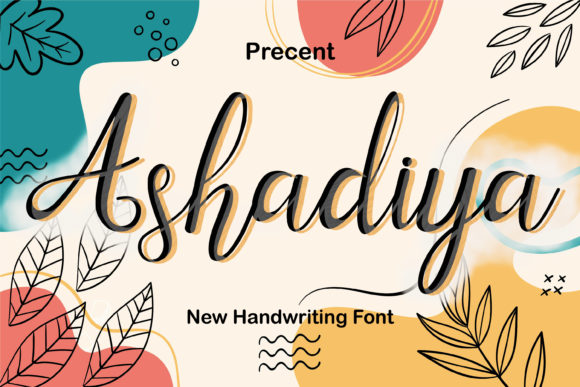
Ashadiya
Ashadiya – A Fonte Script Elegante para Todos os Seus Projetos
Se você busca uma tipografia que combine sofisticação, legibilidade e versatilidade, Ashadiya é a escolha perfeita. Desenvolvida especialmente para embalagens, mockups, convites, flyers, pôsteres de eventos e qualquer criação que exija um toque de alta qualidade, esta fonte script bem‑balanceada transforma ideias simples em designs deslumbrantes.
Por que escolher a Ashadiya?
- Estilo cativante: traços fluidos e elegantes que dão personalidade a cada palavra.
- Alta legibilidade: apesar do visual artístico, a fonte mantém clareza em tamanhos pequenos e grandes.
- Versatilidade total: funciona impecavelmente em embalagens de produtos, convites de casamento, flyers promocionais e pôsteres de eventos.
- Facilidade de uso: pronta para ser aplicada em mockups e apresentações sem necessidade de ajustes complexos.
Aplicações Ideais
Com Ashadiya, você pode criar projetos impactantes em diferentes áreas, como:
- Embalagens de cosméticos, alimentos e bebidas.
- Convites de casamento, festas e eventos corporativos.
- Flyers promocionais para lançamentos de produtos.
- Pôsteres de shows, exposições e feiras.
- Mockups de identidade visual para apresentação a clientes.
Em resumo, Ashadiya é a solução completa para designers que desejam unir estilo e funcionalidade. Seu visual elegante, combinado com alta legibilidade, garante resultados profissionais em qualquer tipo de material de comunicação visual. Experimente agora e deixe seus projetos falarem com a beleza única que só a Ashadiya pode oferecer.